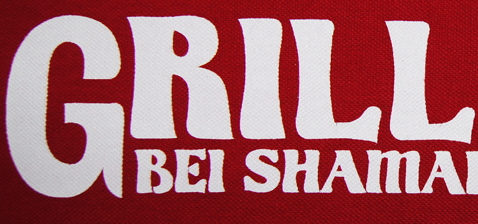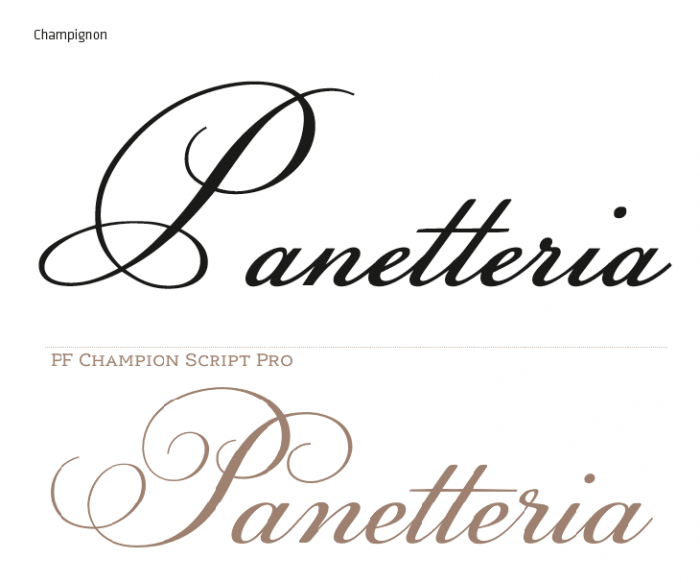
"Panetteria" ist ein Freefont namens Champignon.
Für mich sieht das nicht nach einem Klon aus …
es war nur so eine spontane idee, ob bei der champignon die champion script oder die bickham script auf zweifelhafte weise abgekupfert worden sein könnten. die champignon machte nämlich einen recht professionellen eindruck auf mich, anders als die restlichen 99% ›formal scripts‹ (wie sagt man das auf deutsch?) bei dafont & co. tatsächlich ist es wohl so, dass alle drei schriftarten – champignon, champion script und bickham script – auf denselben bzw. ähnlichen vorlagen basieren, die von joseph champion gezeichnet und von george bickham graviert wurden. der autor der champignon, claude pelletier, scheint ein legitimer schriftgestalter zu sein, der sich auf derartige revivals spezialisiert hat.
es war nur so eine spontane idee, ob bei der champignon die champion script oder die bickham script auf zweifelhafte weise abgekupfert worden sein könnten. …
Ja, das wär auch nicht das erste Mal ;-)
Die Champignon gibt es übrigens auch als "alt swash" mit vielen schönen Swashes …
Ein Font, free for personal use, namens R�ttpick
"Kingthings Organica". Das G stand allerdings wohl etwas zu nah am Grill und ist daher verbogen.